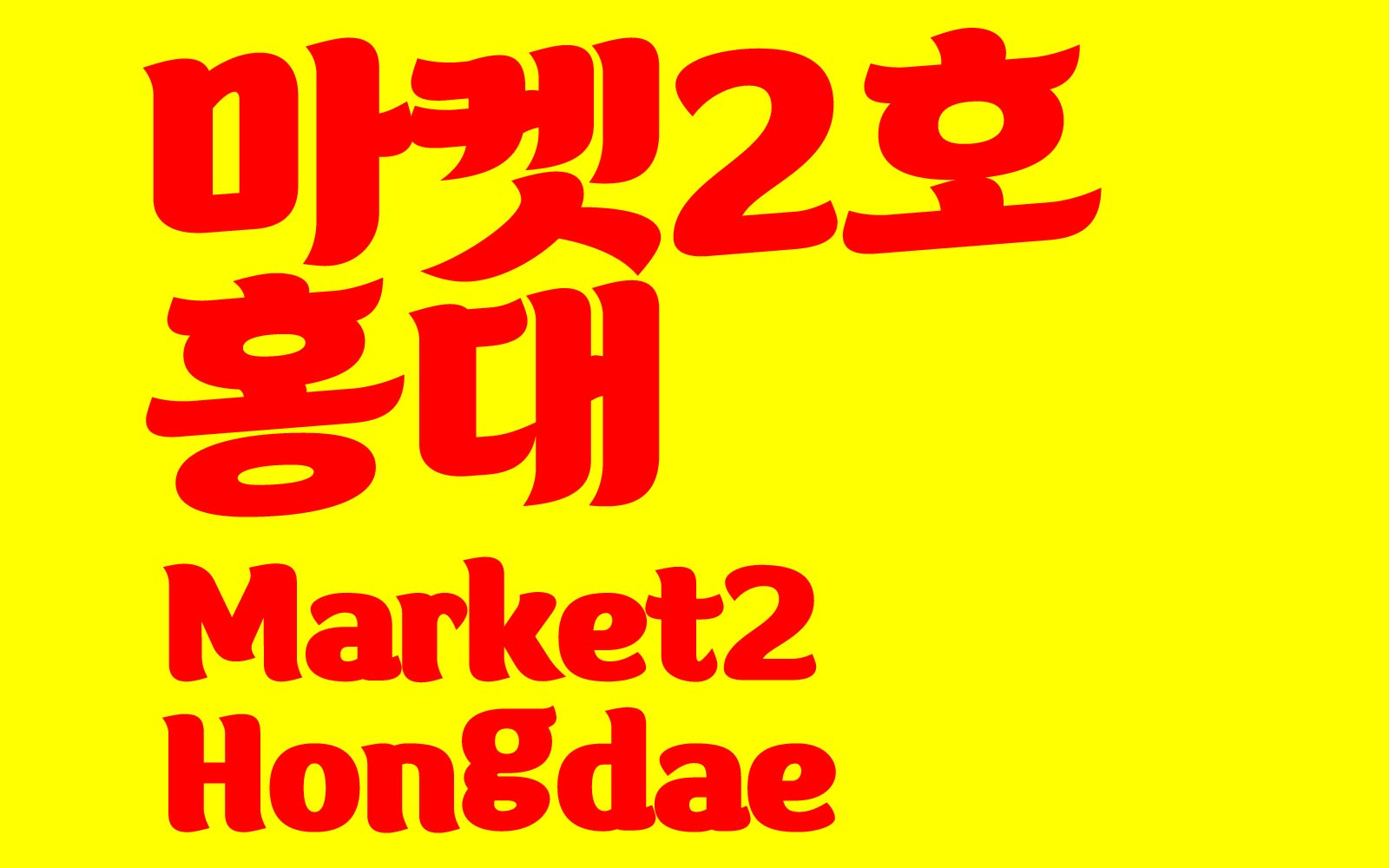
DRMarket2Hongdae
6 Style - ExtraBold, SemiBold, Shadow, ExtraBoldItalic, SemiBoldItalic, ShadowItalic마켓2호 홍대는 홍대의 독특한 문화적 에너지를 부드러운 곡선과 날카로운 형태의 조화로 담아낸 서체입니다. 자연스러운 손글씨 필획에 유럽 ‘살롱’ 문화의 우아함을 더해 감성적이면서도 선명한 존재감을 드러냅니다. SemiBold부터 Shadow까지 총 6종의 패밀리를 제공하며 패키지, 사인, 썸네일 등 브랜딩 전반에 최적화되었습니다. 향후 도시 시리즈로 확장될 감각적인 폰트입니다.
| FontFamily | DR마켓2호홍대점 / DRMarket2Hongdae |
| Design | LeeHo |
| Direction | LeeHo |
| Glyphs | 한글 2,780자 / 라틴 95자 / 약물 986자 / 추가약물 396자 |